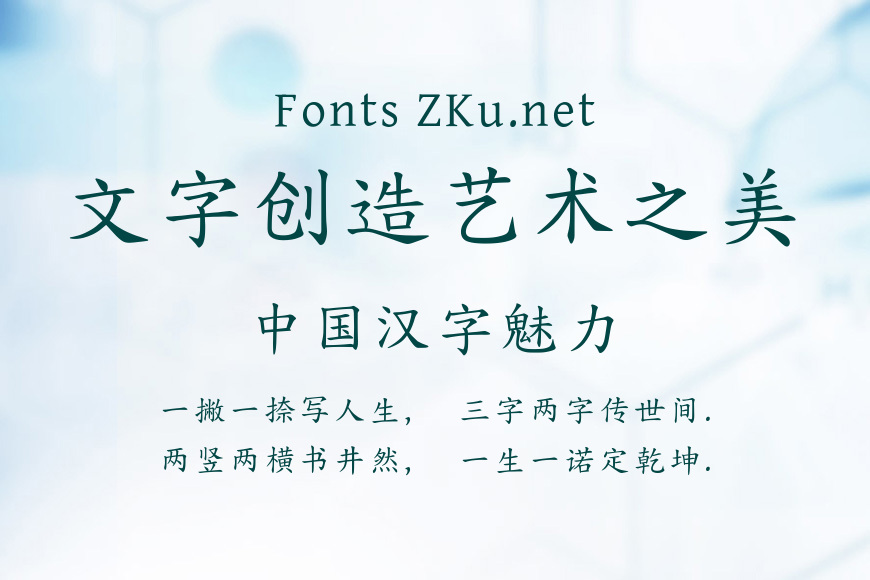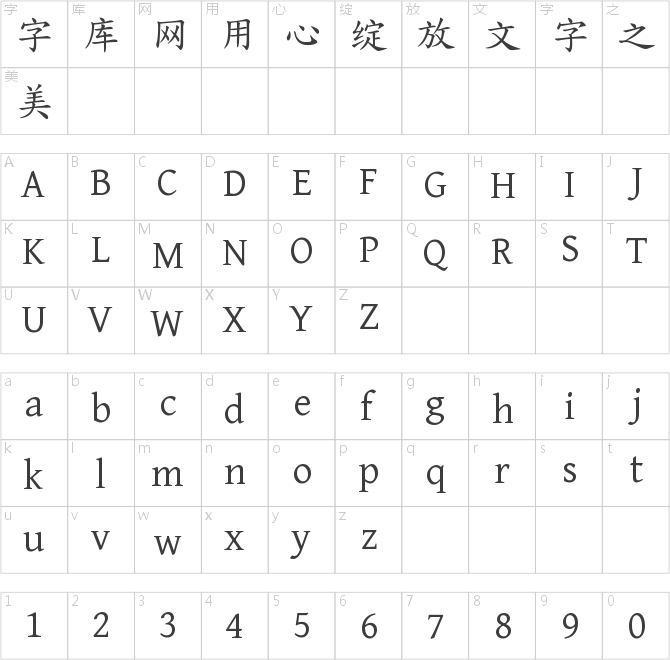
字体名称: 寒蝉正楷体
寒蝉正楷体
寒蝉正楷体介绍
寒蝉正楷体由中文字体《全字库正楷体》和西文字体《Gentium》重新整合优化。全字库正楷体字符非常丰富,还有多语言的支持,成为楷体的优秀范本。但西文部分和中文部分不是特别融合。竖排比横排文字排版更好,个人使用感受。西文字体Gentium是个人最喜欢的西文字体之一,是我认为和楷体搭配最好的西文字体。无论是与文鼎U楷或者其他楷体,整体比原字体西文更加和谐统一。